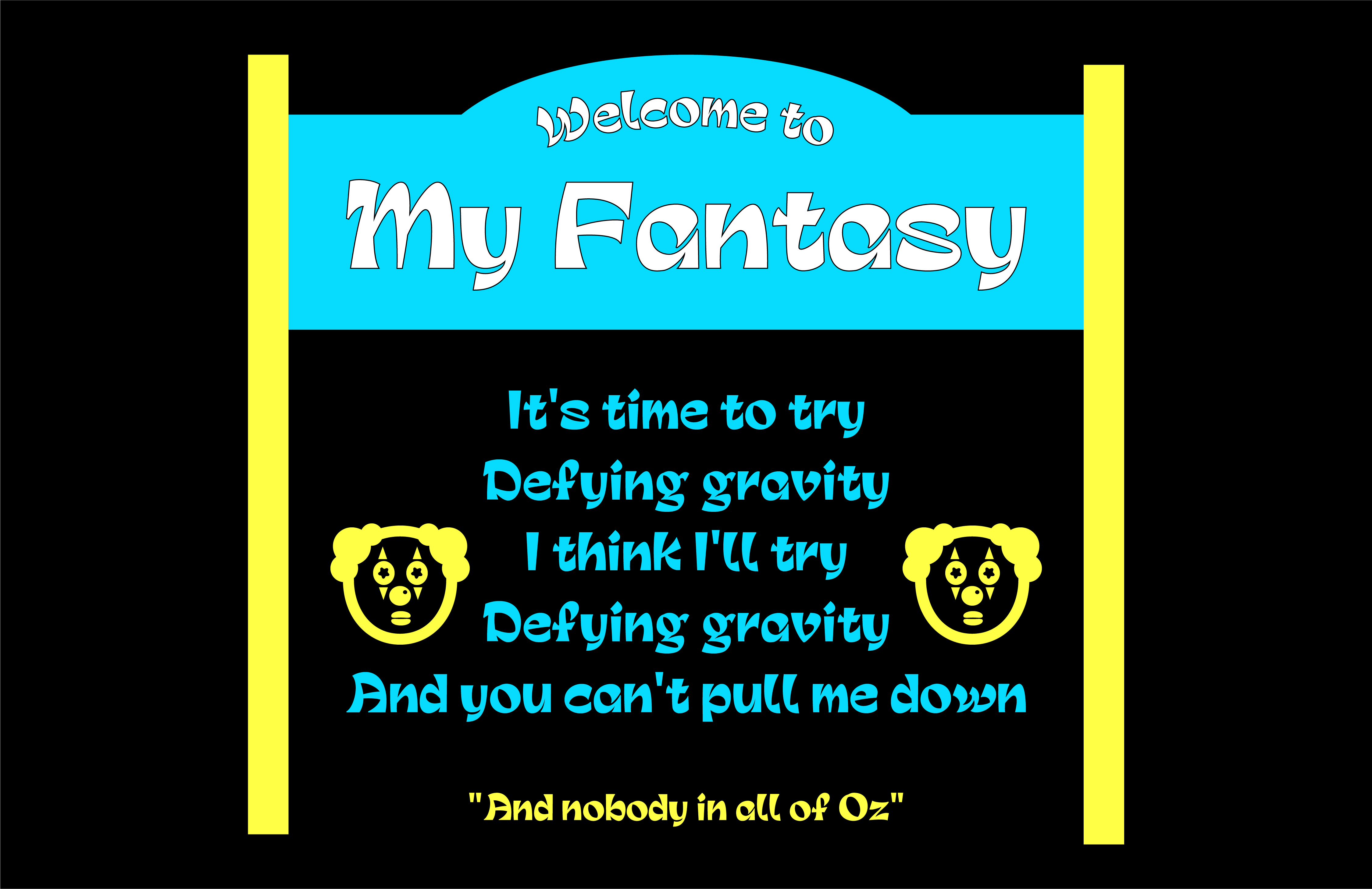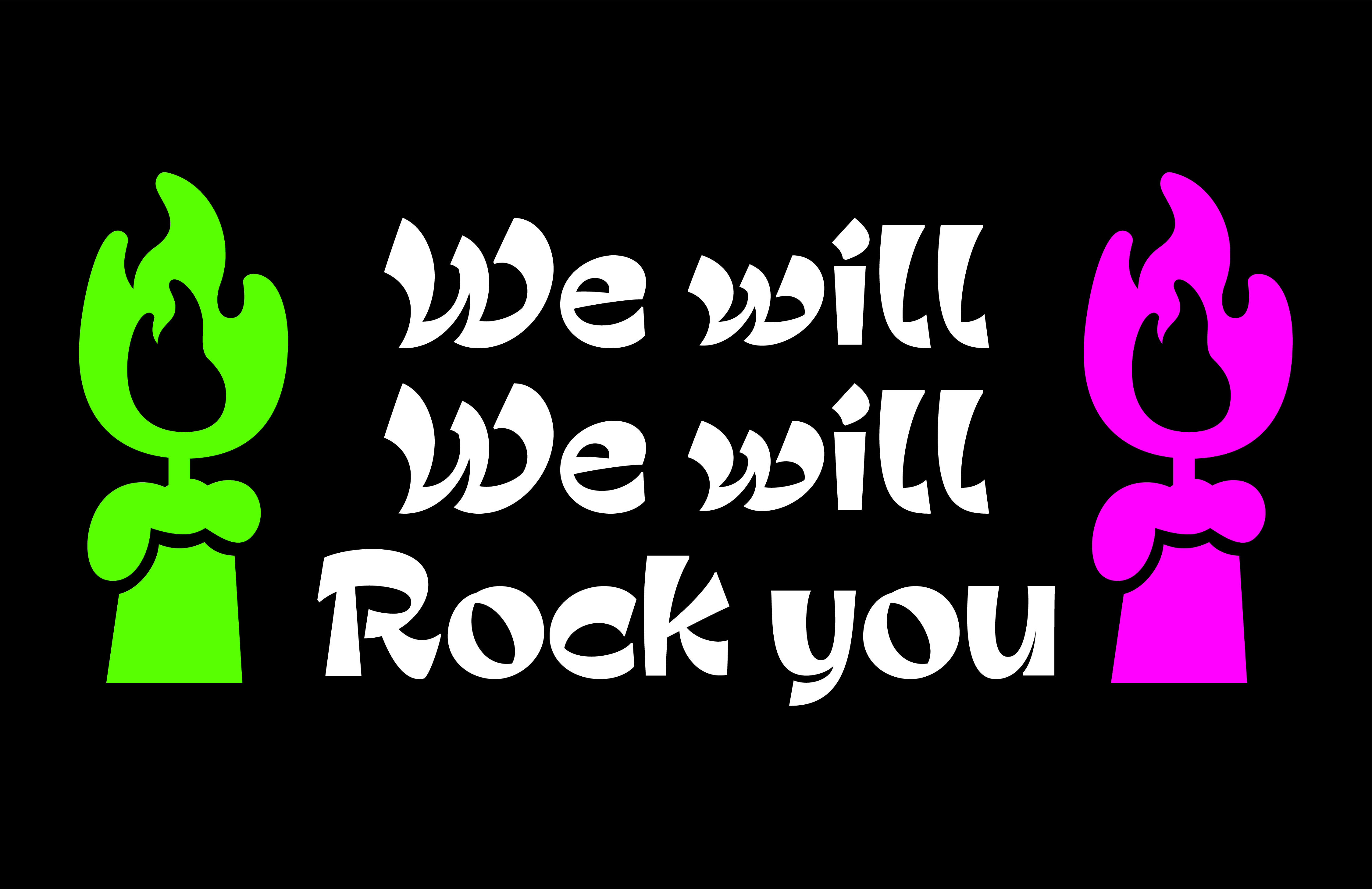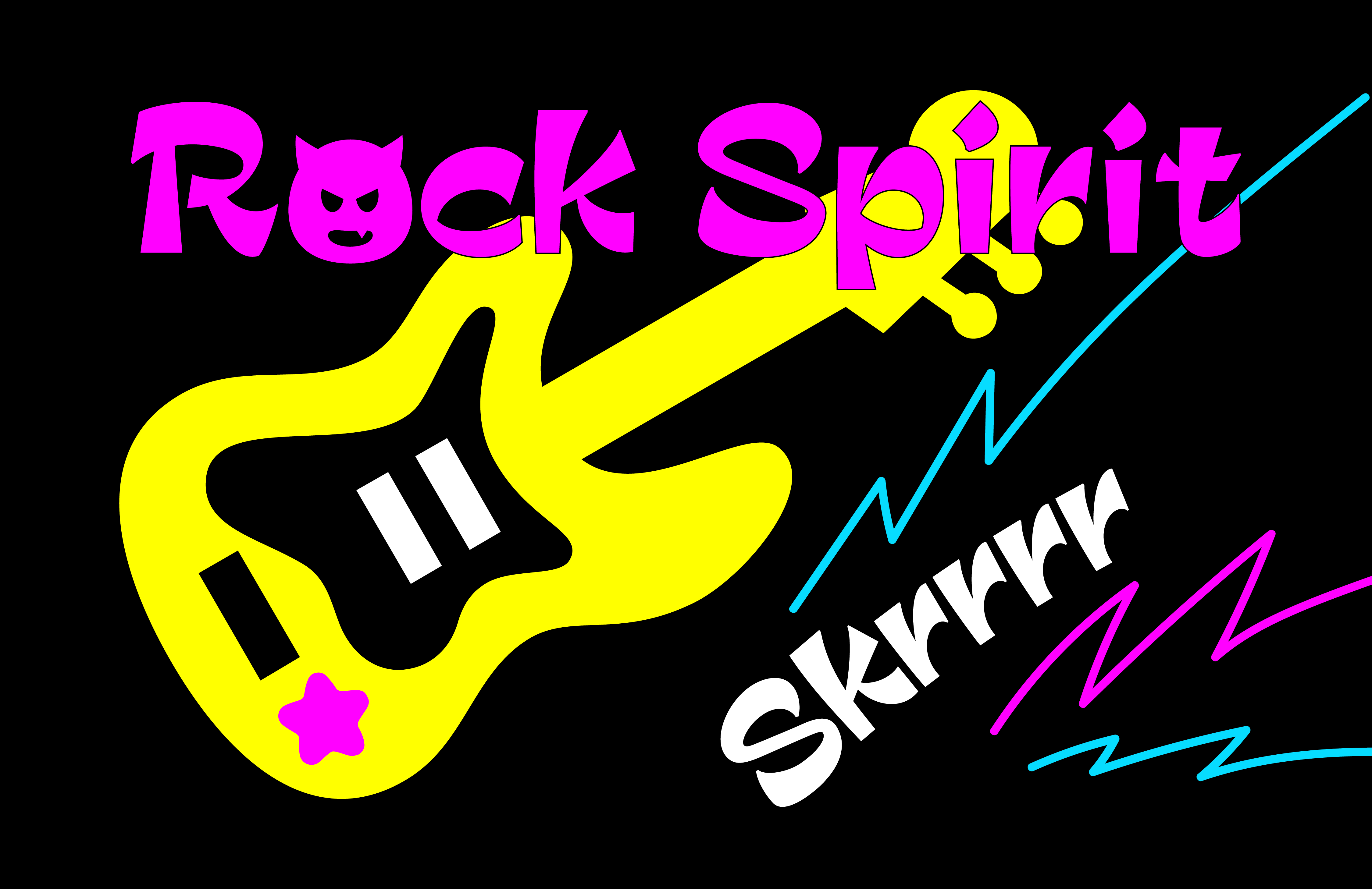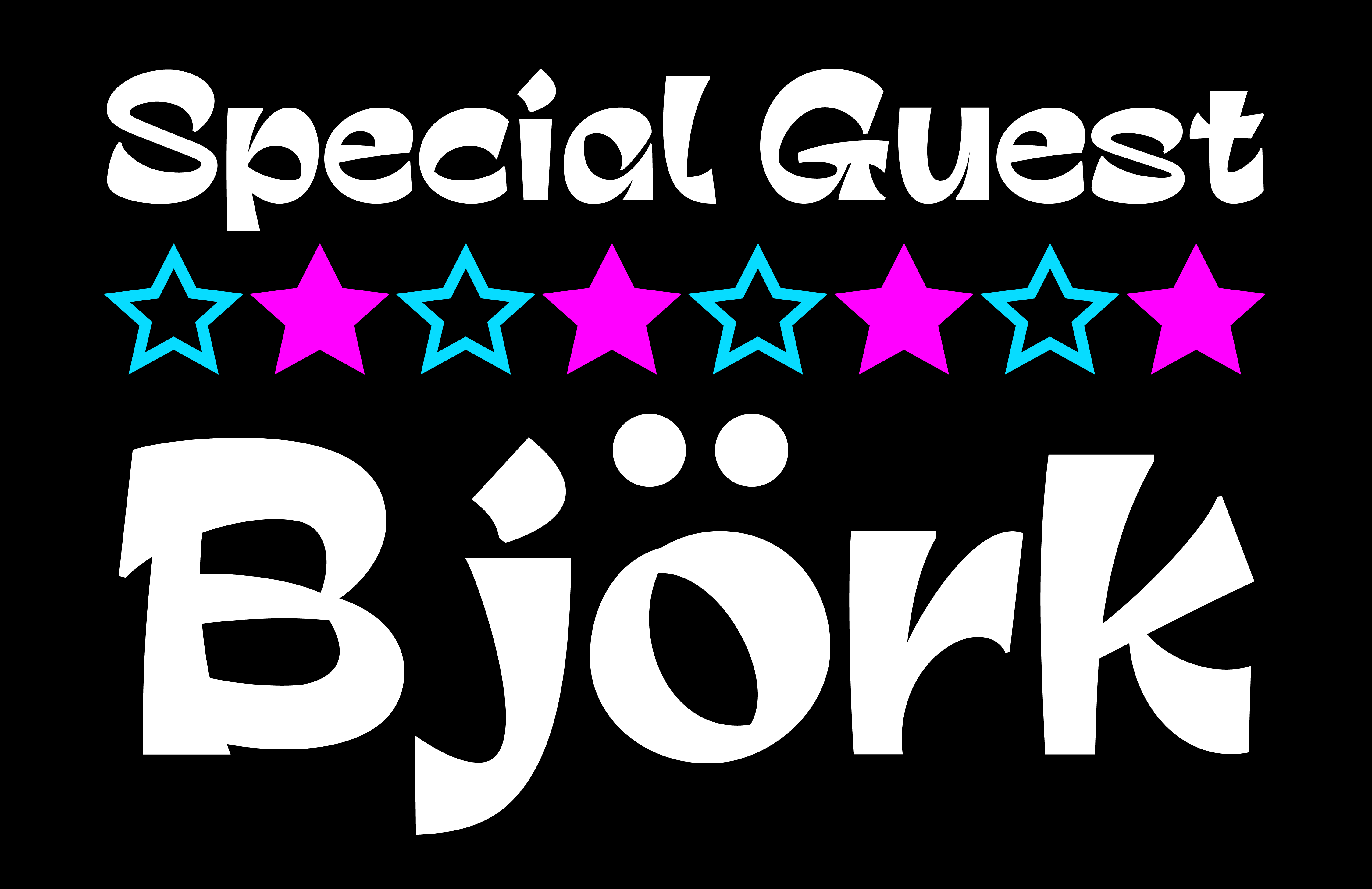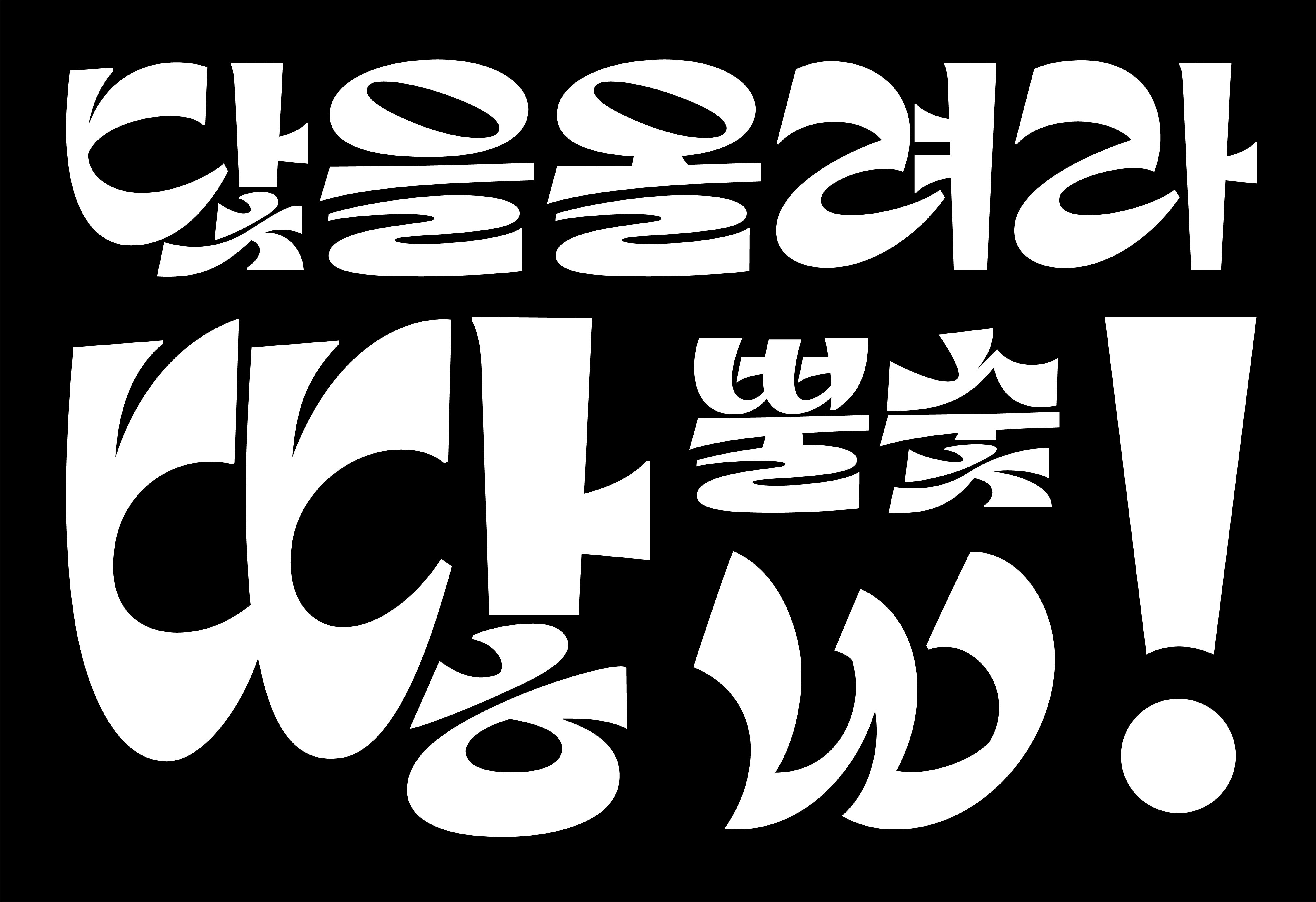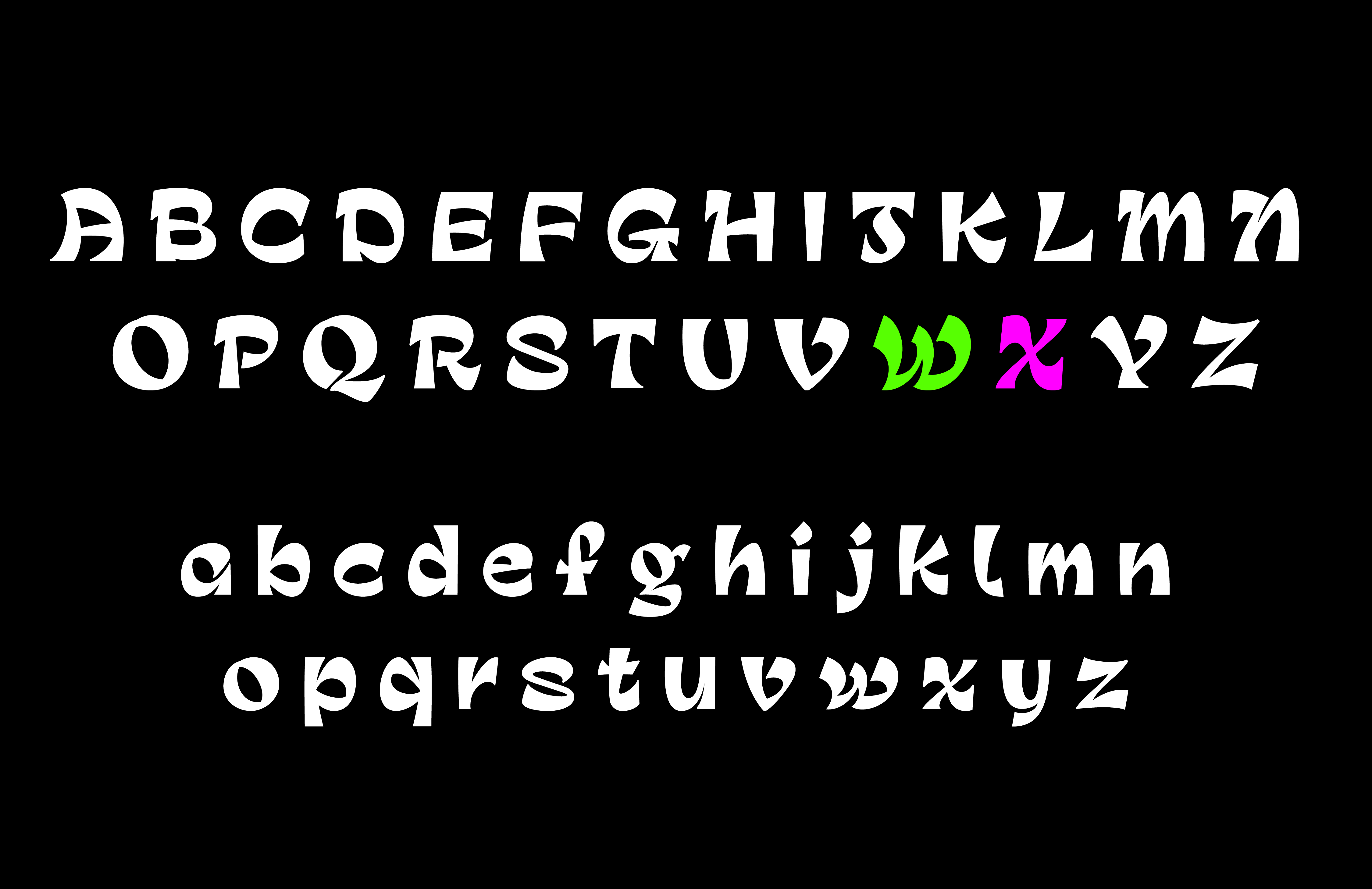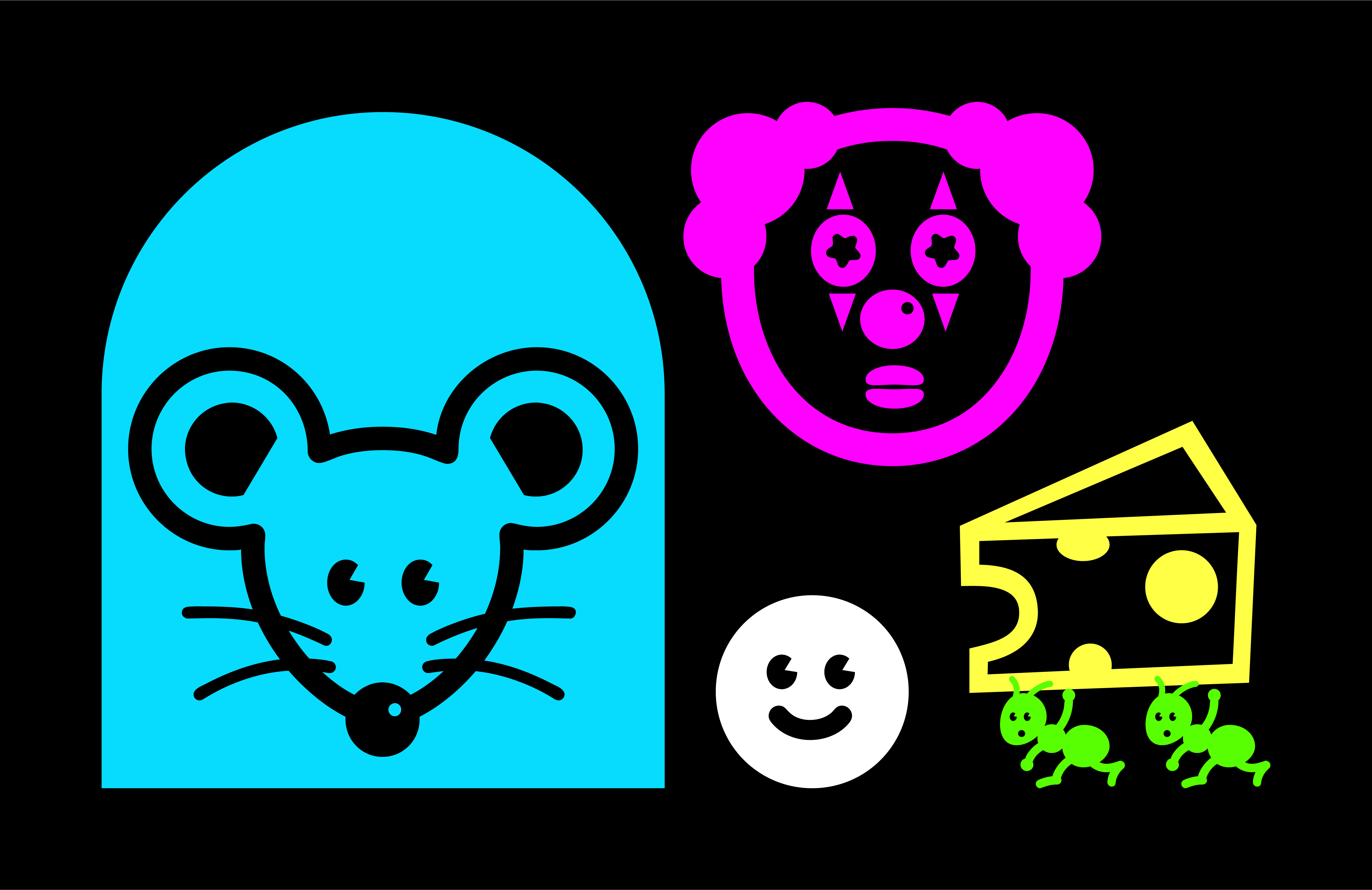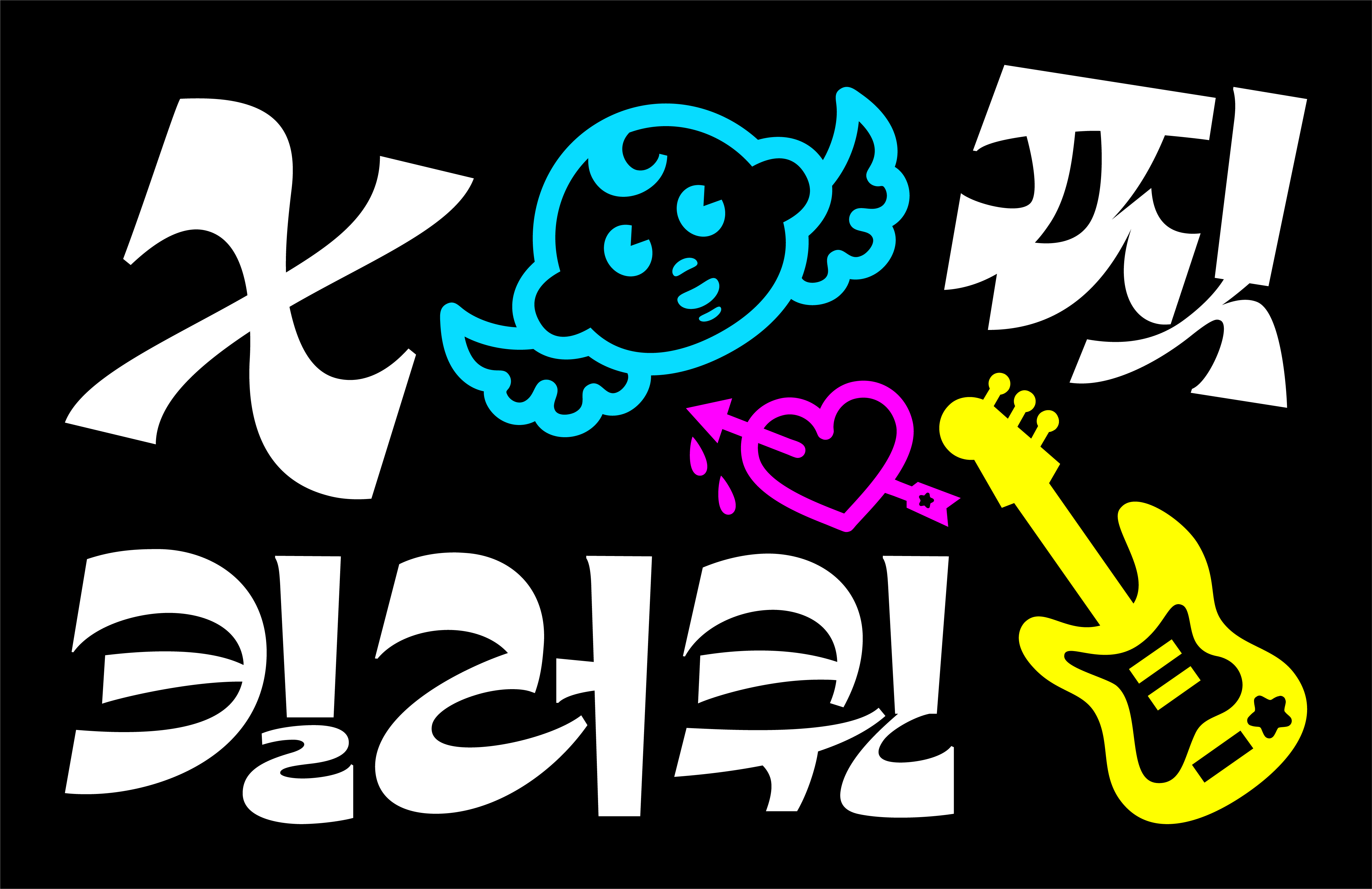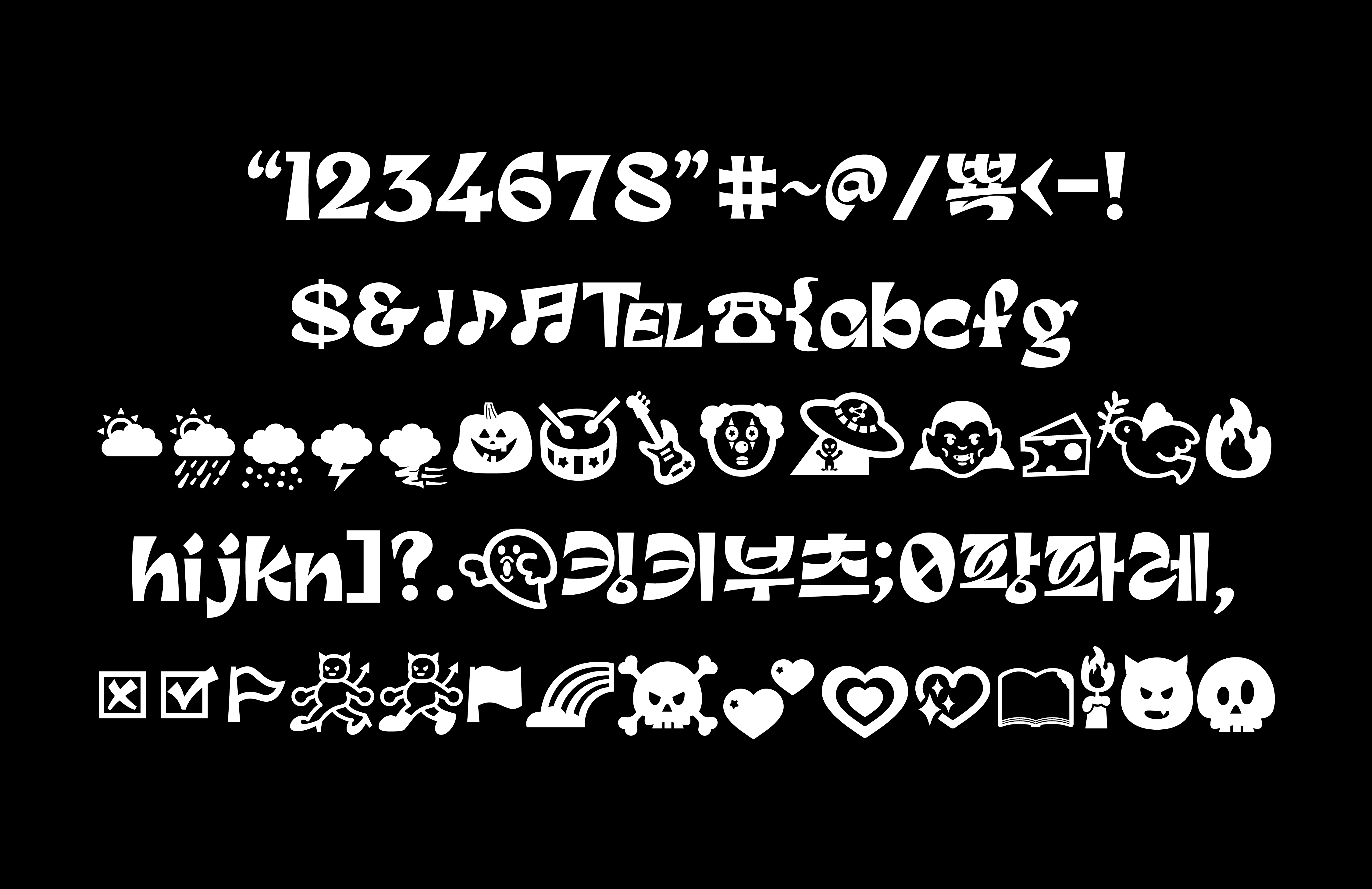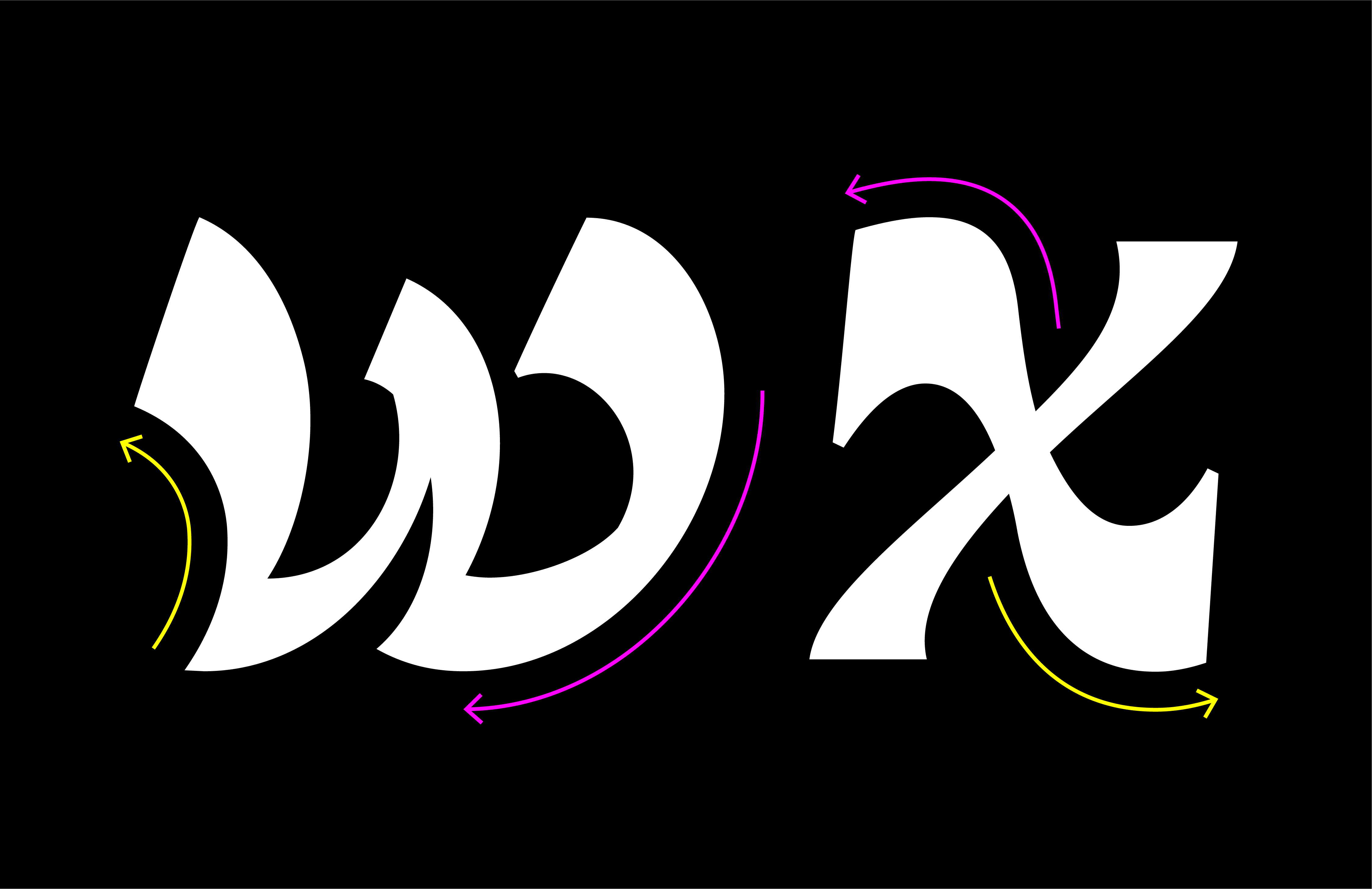
J퍼레이드
종수
1종
Regular
글자수
한글 2,780자
라틴 332자
특수문자 456자
오픈타입 피처
딩벳 55자
디자인 연도
2024
디자이너
송무늬, 이가희
다양한 컨셉으로 활용이 가능하고 독특한 디자인 요소가 많은 서체 시리즈. 개성있는 디테일로 시각적 재미를 더하고 풍부한 이야기를 담을 수 있는 서체이다.
폰트 설명
J퍼레이드는 긴 문장보다는 짧고 강렬한 문구를 외치는 듯한 도전적이고 강렬한 운동감이 특징으로, 다양한 콘트라스트(contrast), 즉 대비가 강조된 글자입니다. [한글] J퍼레이드에는 크게 3가지의 대비가 있습니다. 첫 번째는 자소 크기의 차이입니다. 초성과 종성의 일반적인 크기의 비율에서 벗어나 큰 초성과 상대적으로 작은 종성으로 시각적 긴장감을 줍니다. 두 번째 대비는 획의 차이입니다. J퍼레이드의 획에는 가장 두꺼운 부분이 있다면 가장 얇은 부분이 함께 존재하여 그 차이를 더욱 분명하게 드러냅니다. 마지막 세 번째 대비는 곡선과 직선의 대비입니다. 초성과 종성은 과감한 곡선을 사용했지만, 중성은 그와 반대로 직선적으로 표현했습니다. 이렇듯 J퍼레이드는 다양하고 강렬한 대비들이 모여서 글줄의 흐름이 역동적이며 글자 전반에 느껴지는 흐름은 크게 펄럭이는 깃발이나 파도와도 같은 이미지를 떠올리게 합니다. [라틴] 라틴 글자는 앞에서 설명한 한글과 동일하게 글자 하나로도 강력하고 효과적인 디스플레이 폰트를 만들어보는 것이 목표였기 때문에 한글과 함께 사용할 때도 크기감이 작아지지 않고 하나의 흐름으로 이어지도록 디자인했습니다. 그래서 다른 글자들보다 다소 크게 느껴질 수도 있지만 각 글자의 개성을 유지하면서 조화를 이루도록 만들어진 형태는 다양성이 함께하는 퍼레이드의 연장선으로써 표현됩니다.
[약물] 율동과 운동감에 중점을 두고자 KS특문영역에는 없지만 깃발이나 걷는 사람(pedestrian) 등의 새로운 딩벳들을 추가했습니다. 다양한 형태로 표현된 딩벳들이 모여 차별이나 경계 없이 함께 행진하는 퍼레이드의 이미지를 떠올리게 하며, 볼드한 라인과 캐릭터성이 강한 그래픽적인 표현은 키치하고 독특한 인상을 더해줍니다.